Creative Cloud ホーム画面のフォントについて
はじめてまして。ずーっと気になっていたことがあり質問させてください。
気づいた頃からホーム画面が添付のようなフォントなのです。
なんかかわいいですよね。たぶん正規はこのフォントじゃないですよね…??
ホーム画面のフォントの変更の仕方をご存知の方、教えていただきたいです。
横から失礼します
これ、CSS指定のミスって言うか
Adobe側の検証不足からくるもじゃ『ないか』と思っています
基本的なCSSでのフォント指定が以下のようになっていて
body.windows.locale_ja-JP{
font-family:
"Segoe UI" →macOSには基本入ってない
"Arial"→日本語がない
"Tahoma"→日本語がない
Meiryo→macOSには基本入ってない
メイリオ認識している環境だとメイリオ表示の方も多いかも?
SimSun→繁体 台湾語の明朝体
MingLiu→簡体 北京語の明朝体
Malgun Gothic→韓国語のゴシック
で
上から順にいって
表示可能な
Malgun Gothicで表示している場合は
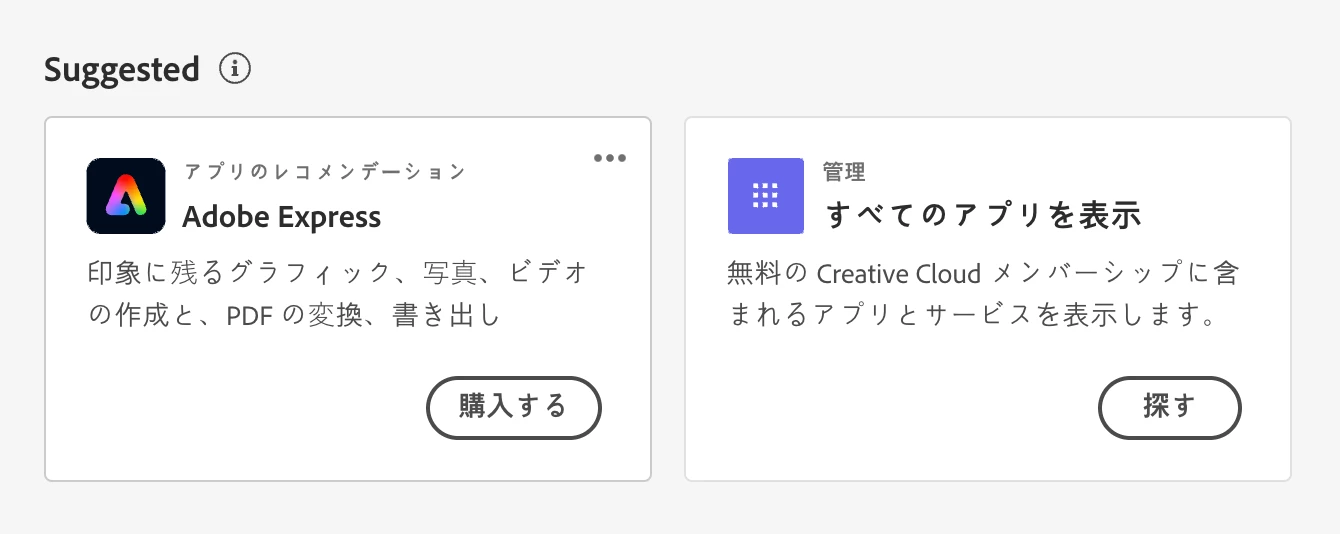
たぶん
chaso43さんのFont環境だとこれが表示されているのかな?と思います
Macって事なので
fontbookでMalgun Gothic停止させれば
たぶんYugoかな?で表示されます
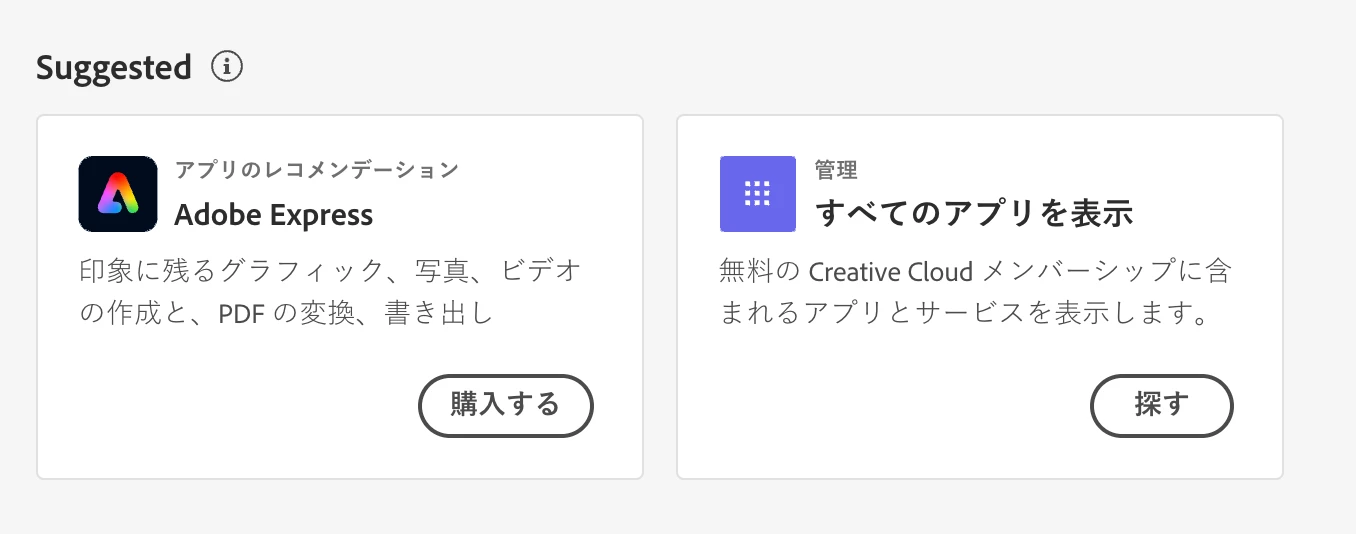
chaso43さんが
Microsoftのメイリオが有効なフォント環境の場合は
メイリオで表示される事がある『かも』しれない…
と
いった感じで
今時のWEB-UIなのに
利用者のフォント環境に左右される表示なんです…遠い目
(なんでAdobeCleanHanで指定しないのか?なぁ?何か理由があるんだろうけど…)
body.windows.locale_ja-JPの代わりになる
body.macos.locale_ja-JPが本来はある『はず』なんだけど
インストールされないからwindows用の表示になっているんじゃないか?と(想像)
こんな言語設定とデバイス無視したCSS
早く治してほしいですよね…
Windows環境の場合、その仕様のデスクトップアプリケーションだとその状態のフォント表示になります。
自分もアップデート後(今年の2/24頃)にその点を気付いて違和感を感じました。
ただデスクトップアプリケーションのUser Voiceがどうも閉鎖されたようなので、不具合や要望の報告自体が現状はできない感じです。
ともあれ、改善されるまでは待つしかなさそうです。
Windows環境のassause様も同じようなフォントなのですね。
私はmacで使用しているのでmac、winの関係はもしかしたらないかもしれないです。
どちらにせよadobeらしからぬ無駄なかわいらしさに開くたびに違和感があり、
どうにか修正してほしいものです…